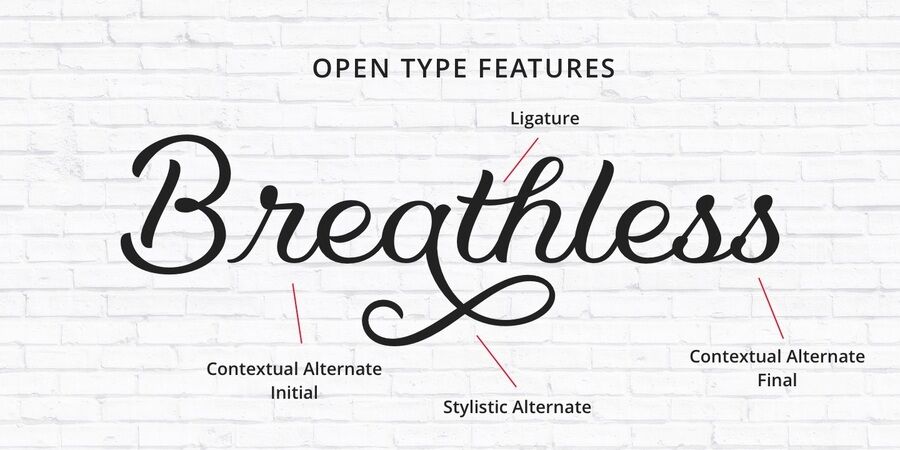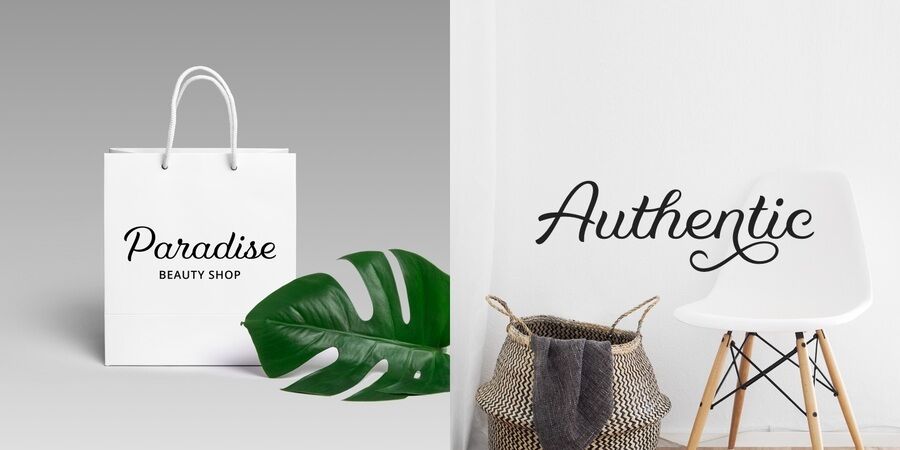
Kamila – це елегантний зв'язний рукописний шрифт. Він заснований на унікальній літерації та виглядає гармонійно в усіх поєднаннях літер. Цей шрифт має понід 900 гліфів та включає 6 наборів стилістичних альтернатив з розчерками, безліч ліґатур та інші open-type фічи. Каміла підтримує більшість латинських мов як в основних, так і в альтернативних формах літер. Шрифт також має початкові і кінцеві форми букв, які з'являються автоматично при введенні, що робить його більш схожим на ручне лист. Кожна буква була ретельно підігнана, щоб з'єднання були гладкими. Каміла відмінно підходить для логотипів, назв, плакатів, журналів, книг, весільних запрошень і поздоровлень. Насолоджуйтесь! Шрифт розробила Віторія Невес у 2017 році.
Асоціації з сімейством шрифтів KamilaОсобистість і характер гарнітури: